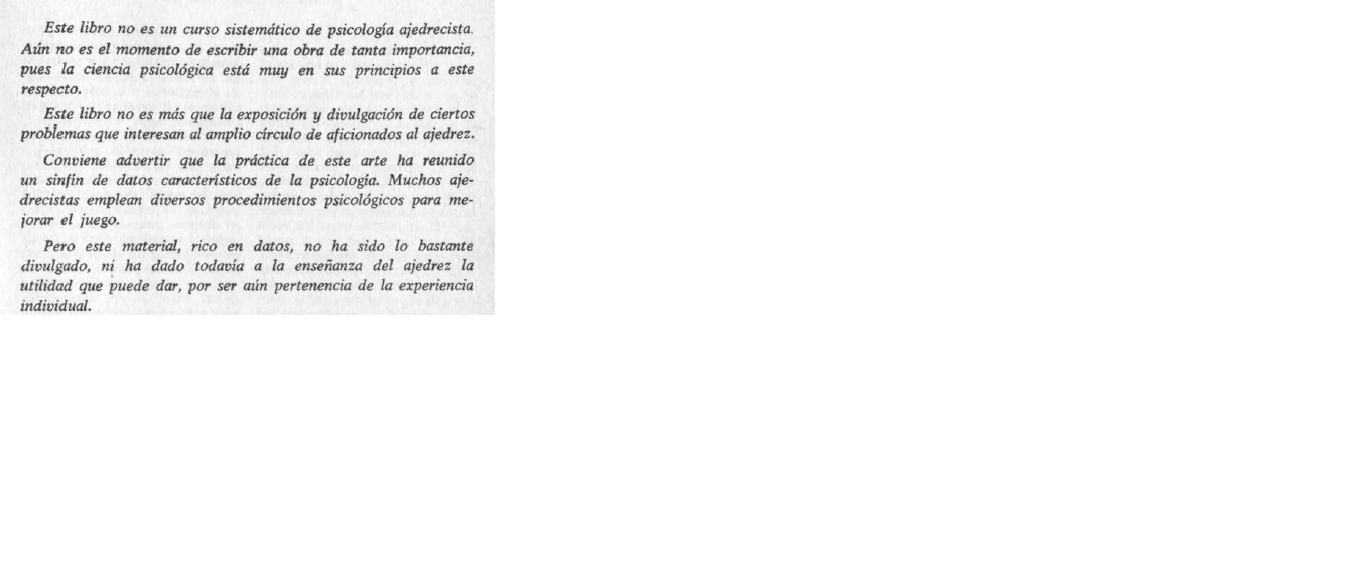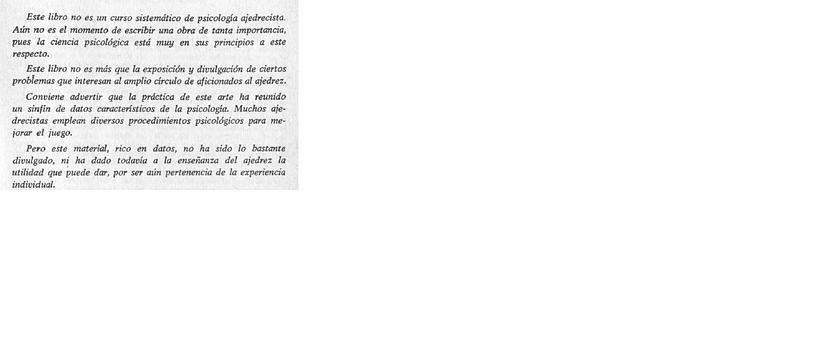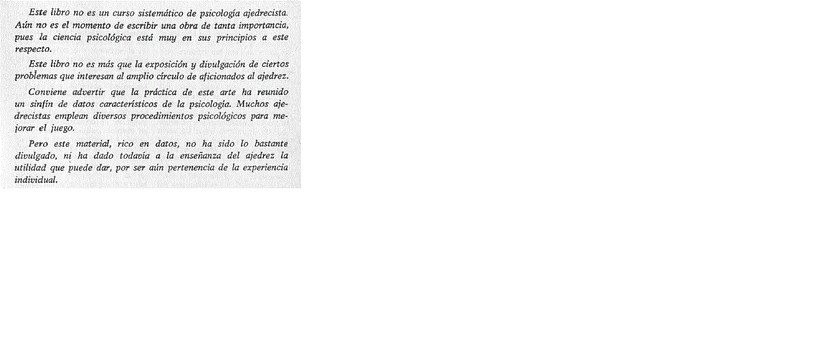
Foro de Tipografía ¿Qué tipografía es esta? el 14.04.2016 a las 03:12 por filebo1974 · 4 comentarios Seguir este tema Dejar de seguir este tema 3 seguidores Hola, querría saber si alguien puede ayudarme con esta tipografía. Está en cursiva. Gracias. Comentar Me gusta
La tipografía es del libro "La psicología en ajedrez" de Nikolai Krogius, Martínez Roca.
nota: es una clásica de lectura, puede que sea una Baskerville o semejante.
A ver si se ve mejor aquí